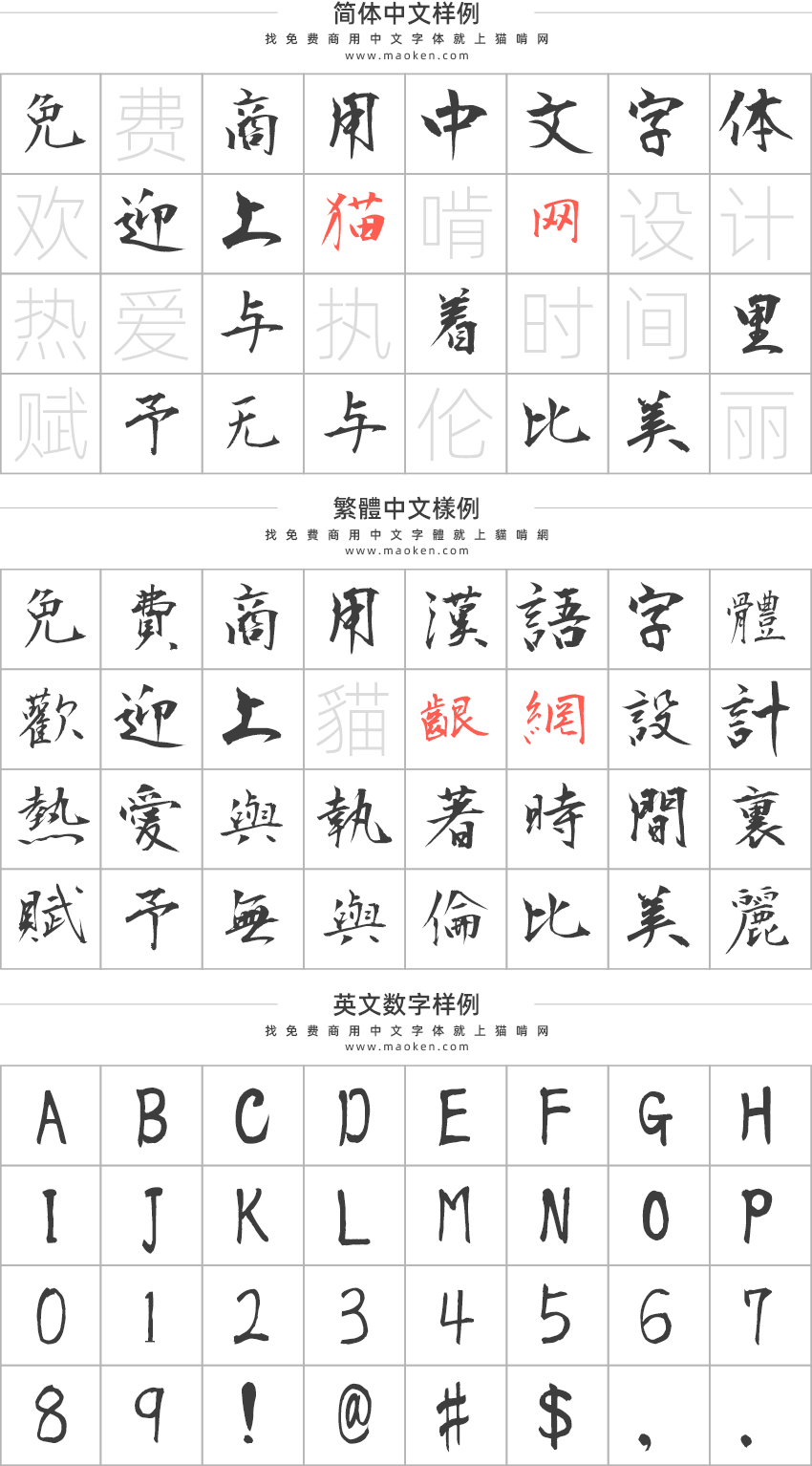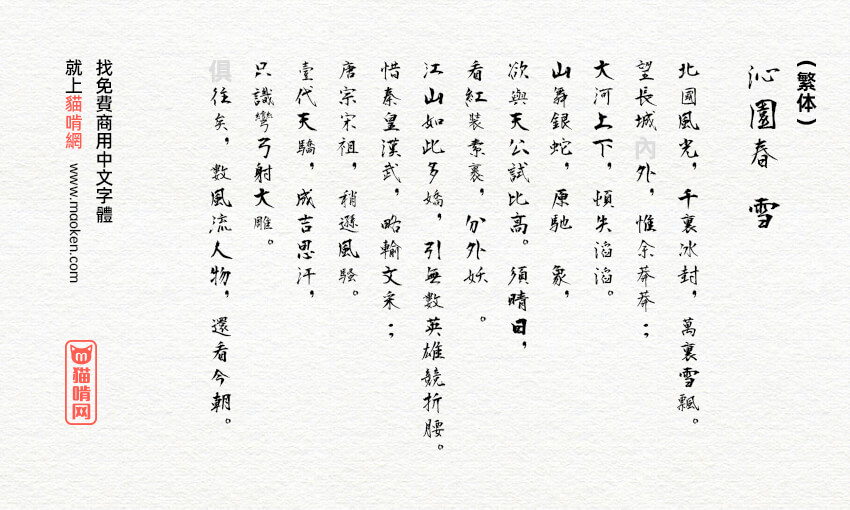
衡山毛笔行书:潇洒飘逸的毛笔书法字体免费商用
字体作者:青柳衡山 (其他语种) 字体字重:1个
字体名称:衡山毛笔行书(日文名: 衡山毛筆フォント行書 )PS中字体名称: 衡山毛筆フォント行書 Regular
衡山毛笔行书是日本书法家青柳衡山先生挥毫写成的毛笔字体,这款字体行笔潇洒飘逸,特别适合海报标题的字体。这款字体包含JIS第1水准2965字,第2水准3390字。由于字体采用的日本的JIS标准,所以支持的简体字数不算多,但是繁体却是比较齐全的。不过目前国内可以免费商用的毛笔字体并不多,中国大陆的只有庞门正道粗书体,马山正毛笔体这两款。所以,这款如果喜欢衡山毛笔行书这款字体,就赶紧下载使用吧。